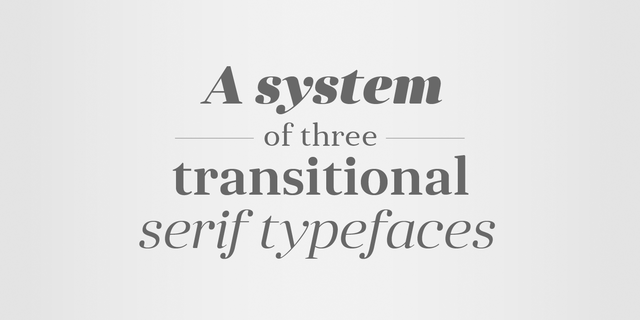
Anglecia Pro — система из трех переходных антикв, предназначенная для использования в печати. Имея общий скелет, вертикальную ось и трапециевидные засечки, каждая из гарнитур имеет разные вертикальные метрики и разный контраст, характерный для разных временных периодов.
Anglecia Pro Text предназначена для набора текста в книжных кеглях. Ее смягченные кривые, уменьшенная высота строчных и длинные выносные элементы придают абзацу традиционную теплую текстуру с легким современным оттенком.
Anglecia Pro Title использует пропорции знакомых переходных антикв, но обладает более выраженным контрастом, что делает ее полезной для набора заголовков, выносок и набора в кеглях от 12 пунктов.
Anglecia Pro Display, обладает ярко выраженным контрастом, тонкими засечками и увеличенными каплями, характерными для современных антикв. Ее большая высота строрчных в сочетании с уменьшенными апрошами предполагает набор в больших кеглях: декоративные заколовки, логотипы, большие выноски.
В общей сложности Anglecia Pro содержит 36 начертаний, каждое из которых поддерживает большое количество языков. В прямых начертаниях кириллица содержит OpenType-альтернативы для придания набору более мягкой (по умолчанию) или более угловатой текстуры. В курсивах эти альтернативы влияют на внешний вид заглавных букв и капители. Каждое начертание содержит широкую поддержку OpenType: лигатуры, капитель, шесть наборов цифр, индексы, дроби, верхние буквенные индексы, вариант пунктуации для набора заглавными.